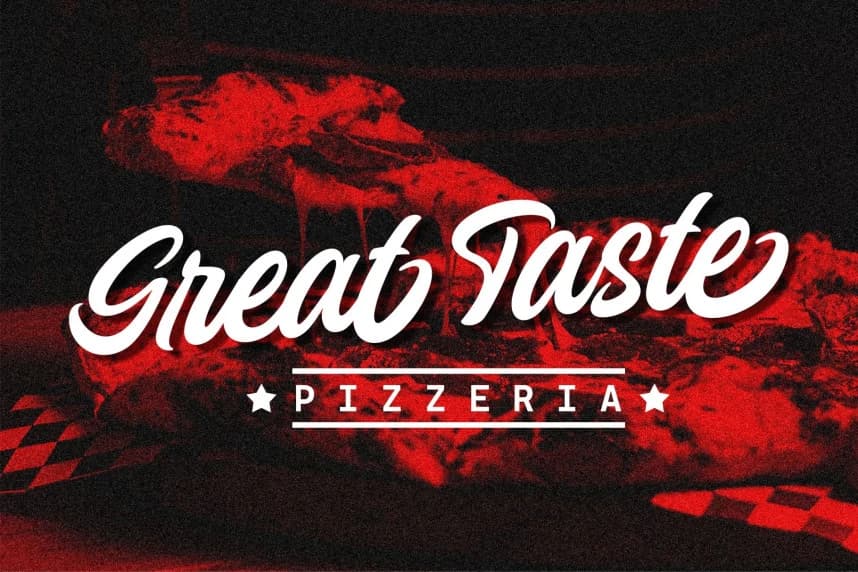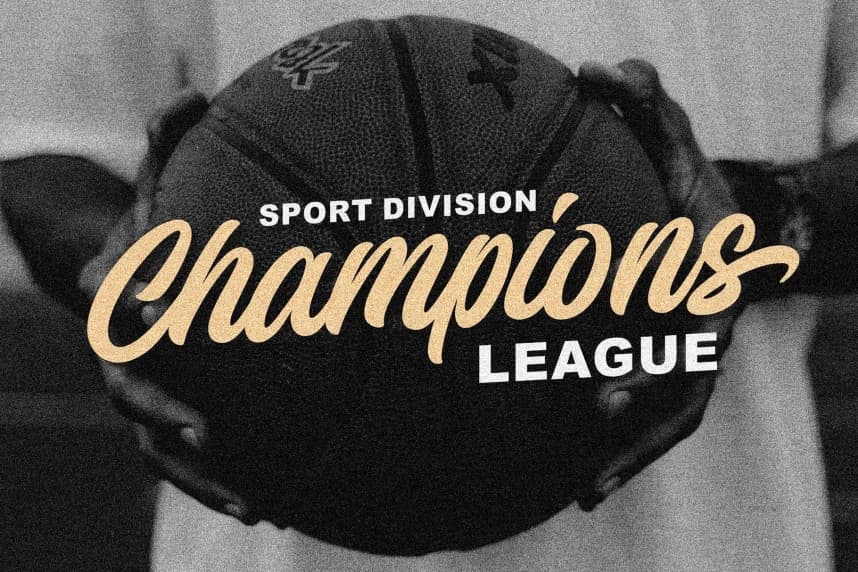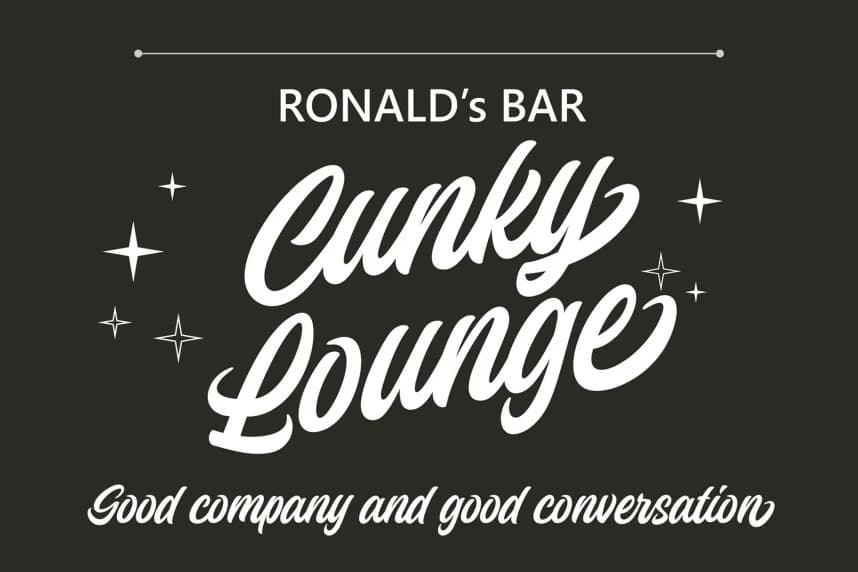
Wilzten Script Font
Wilzten Script Font – Dinamik ve enerjik bir tarza sahip olan şık bir fırça yazı tipidir. Başlıklar, imzalar, logotipler, tişört tasarımları, antetli kağıtlar, tabelalar, etiketler ve haber bültenleri gibi çeşitli amaçlar için kullanılabilir.
Wilzten Script Font – Şık bir el yazısı fontu. Bu dinamik ve enerjik bir stilde harika bir fırça yazı fontudur. Başlıklar, imzalar, logotipler, tişört tasarımları, antet sayfaları, levhalar, etiketler, haber bültenleri gibi çeşitli amaçlar için kullanılabilir.
Wilzten Script
Wilzten Script Wilzten Rv Ezo